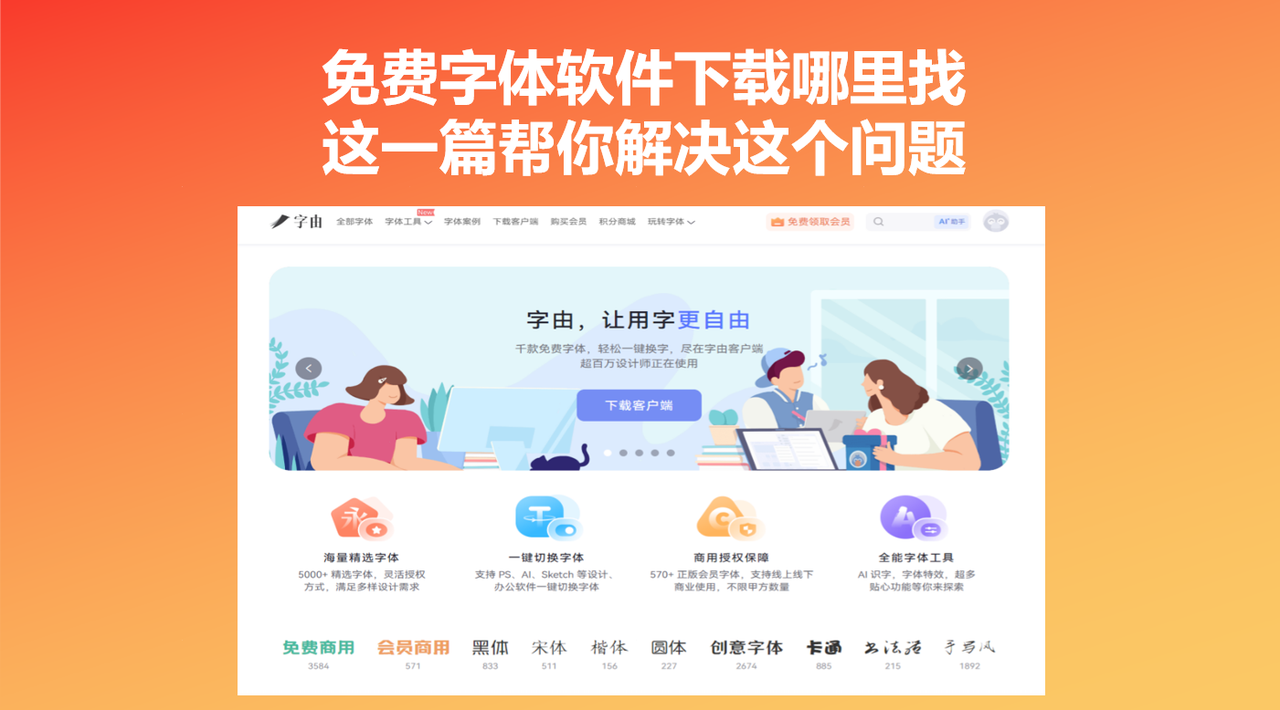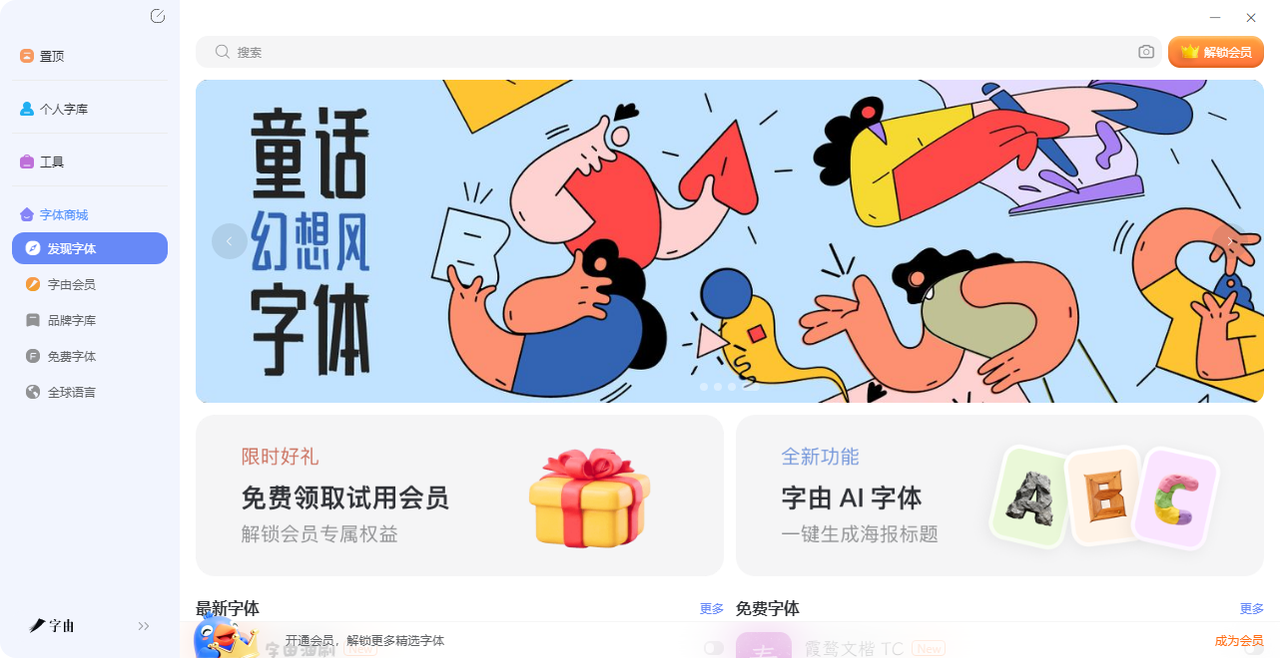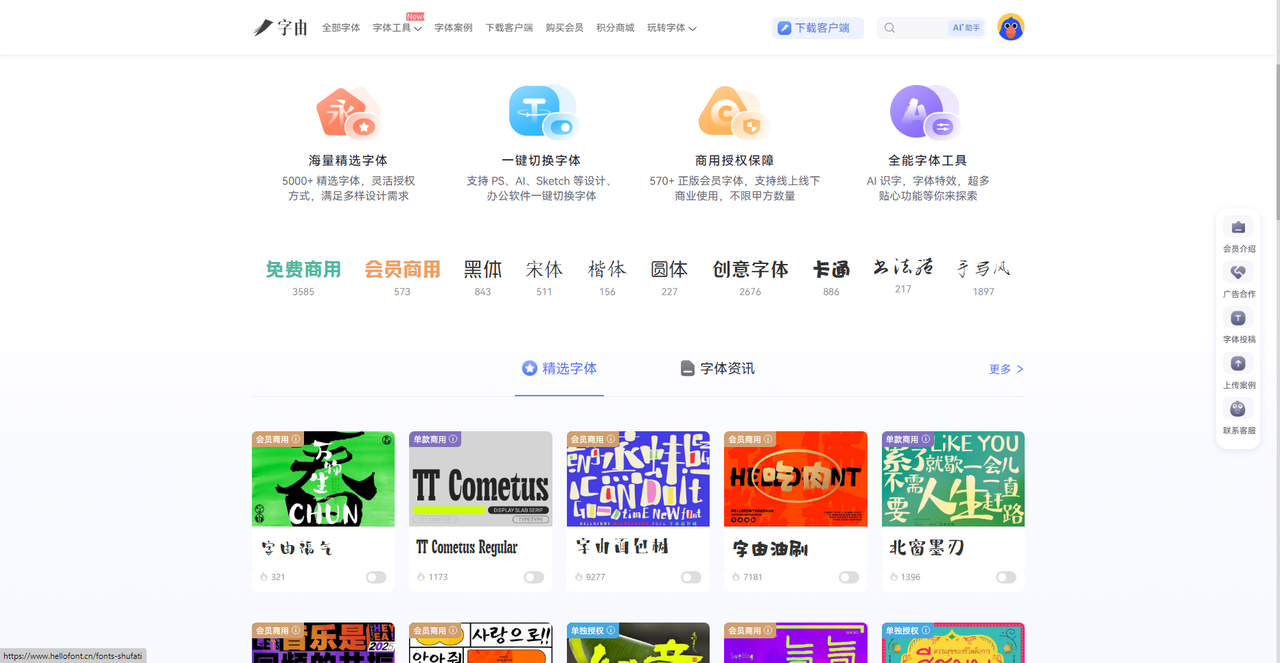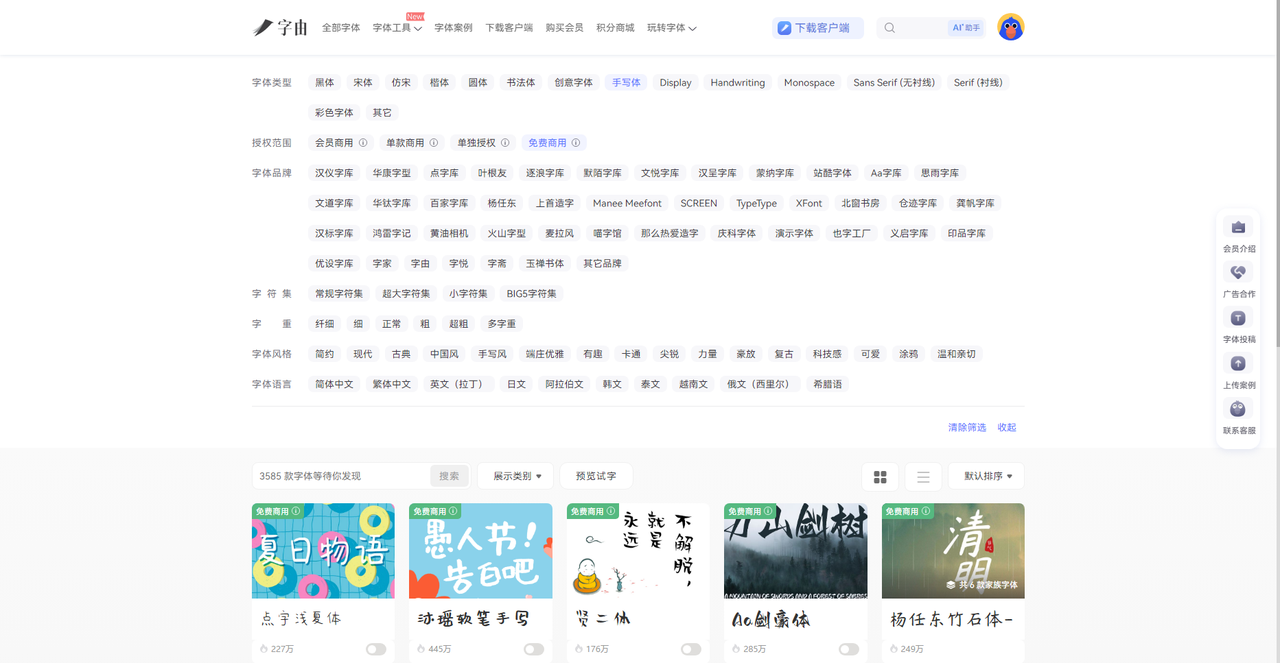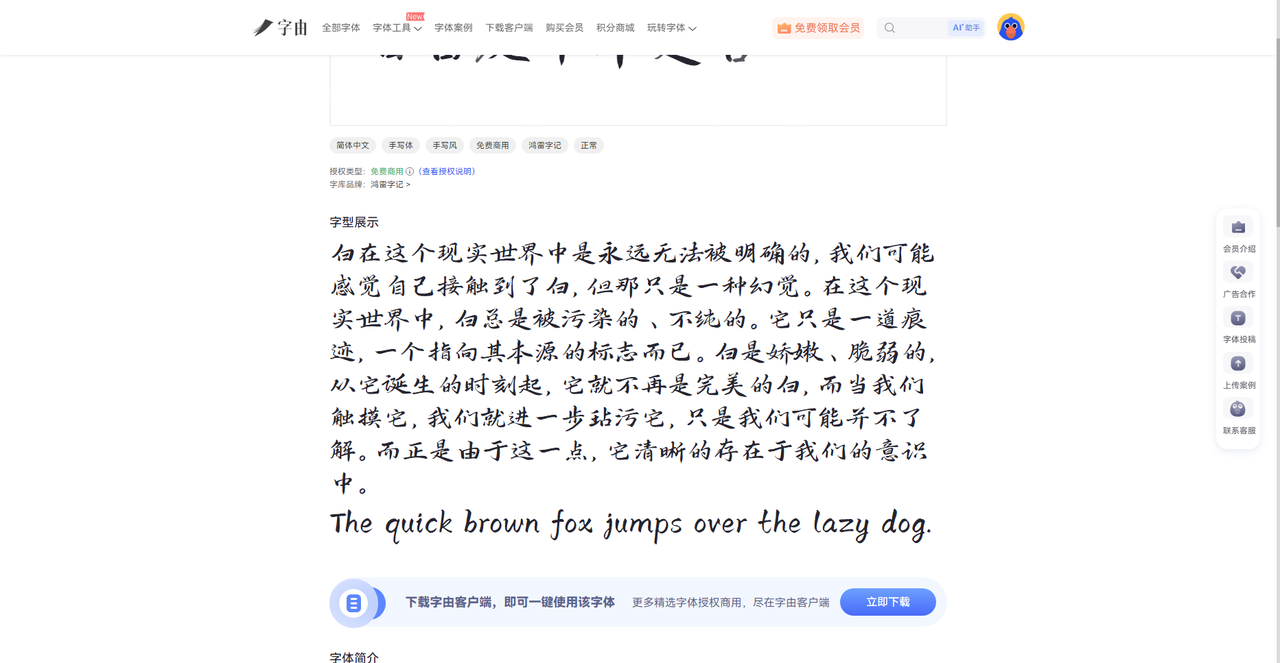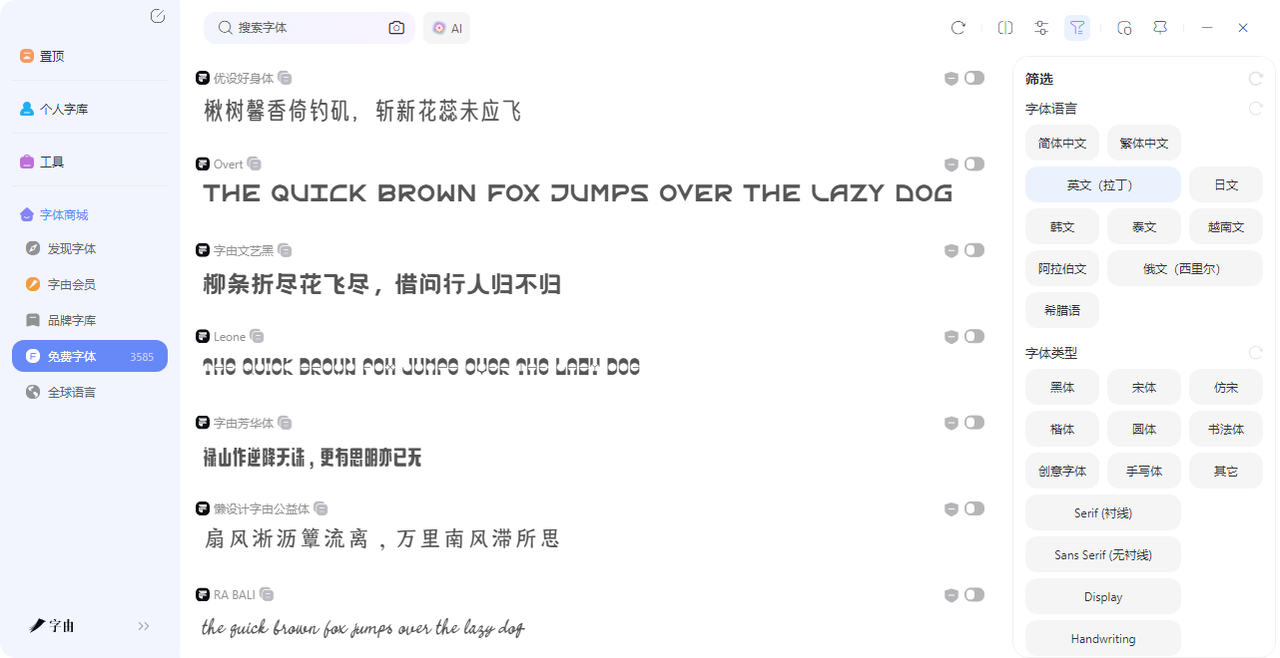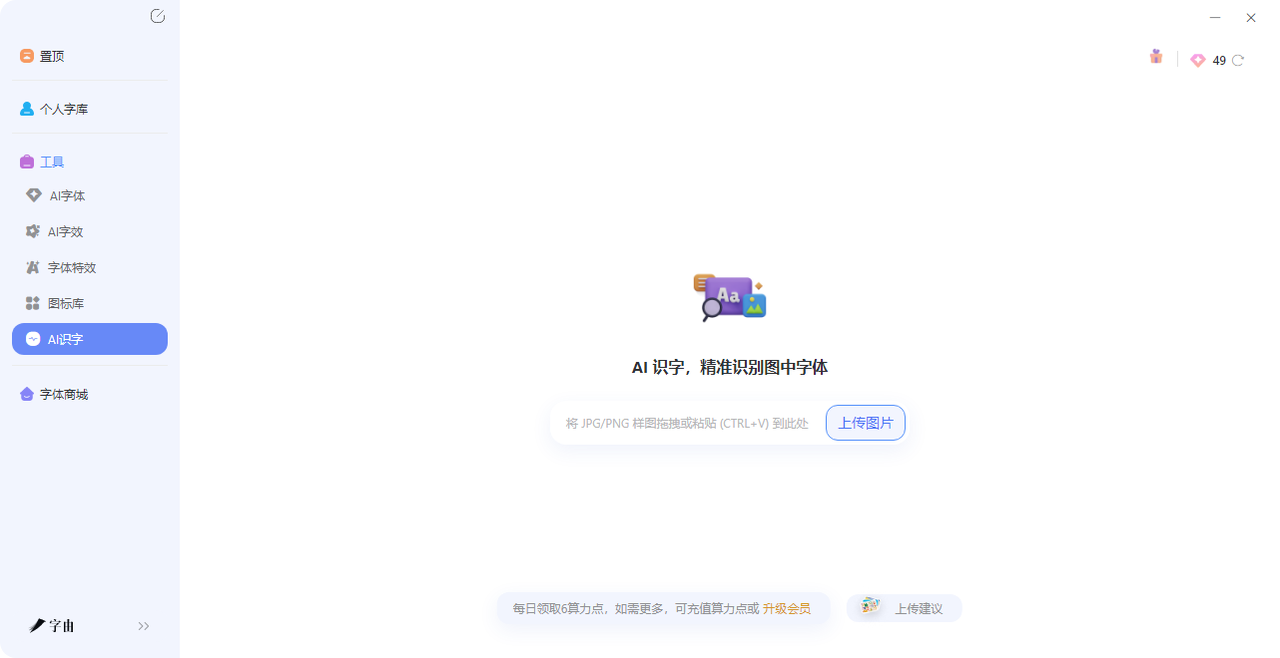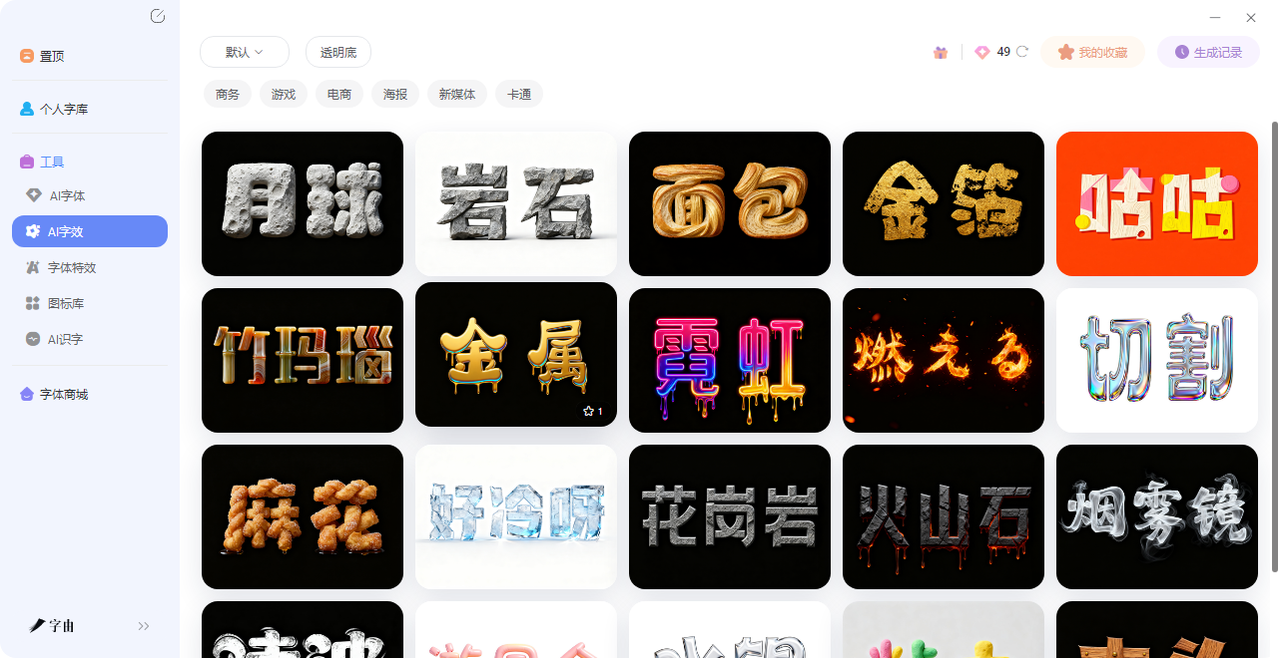
免费字体软件下载哪里找?这一篇帮你解决这个问题
以前设计的最大困难不是没有灵感,而是自己使用的字体不够顺手、找起来又很麻烦,好不容易有一款自己喜欢的结果发现这个字体需要付费下载,这样折腾下来费时又费力。后来我才发现找字体这件事根本不用这么折腾。尤其是在我下载了字由以后,“字由”这款免费字体软件,下载之后,打开就能用,不用安装字体包,不用重启软件。今天这篇就专门讲它的用法——从客户端下载,到网页端使用,再到那些你可能没注意到的隐藏功能,一次性安利给大家。
2、字由网页端-无需下载也能够使用
如果说你不太确定这款软件是否适合你,不想马上安装客户端,字由的网页版也能满足基本需求。网页版适合快速浏览字体,或者临时需要找一款字体用。下面介绍免费字体软件下载的网页端使用方式。
• 第一步:打开字由官网,不用下载,直接就能用。首页就能看到字体推荐和分类。
• 第二步:网页版的字体库和客户端是同步的,同样收录了超过10500 款字体,其中3585 款是免费可商用的。左侧有筛选栏,可以按类型、按授权、按热度快速定位。比如你想找“免费商用”的手写体,点“免费商用”再点“手写体”,系统就会筛出所有符合条件的字体。
• 第三步:找到感兴趣的字体,点进去,可以看到详细的预览。输入你自己的文案,比如“春日来信”“开业大吉”,实时看效果。不用下载,不用安装,看一眼就知道合不合适。
不过网页版也有一定的局限,网页版只能预览字体,无法直接应用到设计软件里。如果你想真正把字体用到PS、AI里,还是得下载客户端。但用来快速找字体、确定方向,网页版完全够用。
3、字由客户端核心功能
字由客户端才是解锁更多玩法的核心,下载了客户端之后,你才算真正用上了字由。下面分几个模块,把它的核心功能挨个讲清楚。
1.免费可商用字体一抓一大把
字由目前收录了超过10500款字体,其中3585款是免费可商用的。这个体量意味着什么?就是你日常设计需要用到的黑体、宋体、书法体、手写体、艺术体,基本都能在这里找到。关于筛选标签:
• 按类型:点“全部字体”,左侧有“黑体”“宋体”“书法体”“手写体”“Sans Serif”“Serif”等分类
• 按授权:直接点“免费商用”,3585款随便挑
• 按热度:每款字体右下角有使用次数,优先选热度高的
• 按品牌:汉仪、蒙纳、Aa字库等官方合作品牌专区,品质有保障
2.几款热门好用字体推荐:
• 优设好身体(503万次使用):方正饱满,适合正文排版
• 字由文艺黑(1436万次使用):既有黑体稳重又带手写感,适合标题、海报
• 沐瑶软笔手写(445万次使用):圆润治愈,适合温暖治愈类内容
• 点字浅夏体(227万次使用):清新手写,适合旅行vlog封面
3.一键应用字体到设计软件
字由最核心的功能,就是在PS、AI、Figma、Sketch、CDR这些软件里一键切换字体。不需要下载安装包,不需要重启软件,选中文字,点一下,立刻换字体。
具体操作:
• 打开PS(或其他设计软件),新建一个文件,用文字工具输入一段文字,选中这个文字图层。
• 打开字由客户端,在字体库里找到你喜欢的字体。
• 直接点击字体——神奇的事情发生了,PS里的文字瞬间切换成该字体。
当你纠结于选哪款字体时,这个功能尤其好用:点一下换一款,哪款合适一眼就能看出来,试一款字体只要1秒钟。这才是真正的“用字自由”。
4.个人云字库:你的字体管家
以前最烦的事就是换电脑,收藏的字体全没了,得重新下。字由的个人云字库功能,可以把本地字体上传到云端。换设备登录,字体自动同步。不用U盘拷来拷去,也不用担心电脑坏了字体丢失。在客户端左侧找到“个人云字库”,点击上传,把你本地收藏的字体文件拖进去就行。上传后,其他设备登录同一个账号,就能直接激活使用。
5.AI工具辅助设计
字由还有很多实用的AI工具,专门帮设计师解决日常杂活:
• AI识字:看到一张海报上的字很喜欢但不知道是什么字体?截图上传,AI帮你识别名字和授权类型。认出来之后,如果字由里有同款,旁边会有“使用”按钮,点一下就能直接调用。
• AI字效:如果你已经有了一款基础字体,想给它加个特效,比如发光、金属、水彩,可以用AI字效。内置400多种特效模板,点一下就能加,不用自己调图层样式。
• AI擦除:想去掉图片上的文字又不想慢慢修?上传图片,AI识别文字并擦除,背景自动补上,几秒钟搞定去水印、改文案这些事。
找字体可能不能不难,但是想找到高质量免费可商用字体是个难事,但是自从有了字由这样的免费字体软件,你只需要下载客户端,打开就能用。从筛选字体到一键应用到设计软件,从个人云字库到AI工具,它把和字体相关的所有事都打包在了一起。如果你也在为找字体发愁,不妨试试字由——免费下载,免费使用,用着顺手才是硬道理。